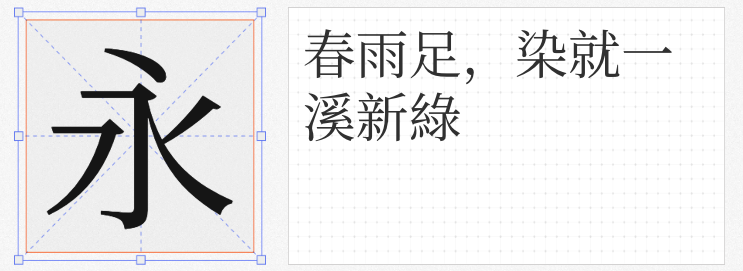
在东方设计语境中,宋体字以其独特的文化基因与视觉张力,始终占据着重要地位。本文精选四款免费可商用的高质量宋体,涵盖古籍修复、现代标题、屏幕适配等多元场景,助力设计师在商业项目中实现文化表达与实用功能的平衡。
1. USMCC源简特粗体
作为思源宋体的反向插值创新体,这款字体以特粗字重打破宋体"纤细"的刻板印象。其笔画粗细对比强烈却不失宋体结构精髓,特别适合作为标题与正文字重的搭配组合。设计师巧妙保留了思源宋体的多语言支持特性,在繁简中文、日文、韩文等场景中均能保持视觉和谐,是海报、包装等需要视觉冲击力的场景的理想选择。
2. 源古宋体
由《真·國標繁體-古籍規範字形工具包》衍生出的专业字体,完美解决古籍印刷规范字形的实践难题。基于思源宋体骨架,融入文津宋体的传统韵味,对B区扩展字符进行系统化整理。设计师特里王通过部件统一策略,既保留了古籍用字的历史层次感,又实现了现代排版的规范性,堪称学术出版、文化展陈领域的首选字体。
3. 纳米老宋
以汇文明朝为基底,融合遍玨体笔意,这款补充字体在保持宋体基本特征的同时,通过笔画粗细的微妙调整,营造出古朴而不失现代感的独特气质。其设计团队通过复合修改技术,解决了传统宋体在数字显示中的锯齿问题,特别适合文化创意产品的品牌标识设计。
4. 香萃等粗宋
这款字体以"等粗"概念重构宋体美学,通过0.8:1的横竖比例设定,在保证屏幕可读性的同时,维持了纸媒的优雅质感。中宫收紧的设计语言赋予文字内敛气质,而平滑的笔画转角则传递出温暖的人文关怀。其20000+字符库覆盖泛中日韩表意文字,新旧字形混合使用的策略,既满足学术严谨性需求,又兼顾了传统文化的传承。